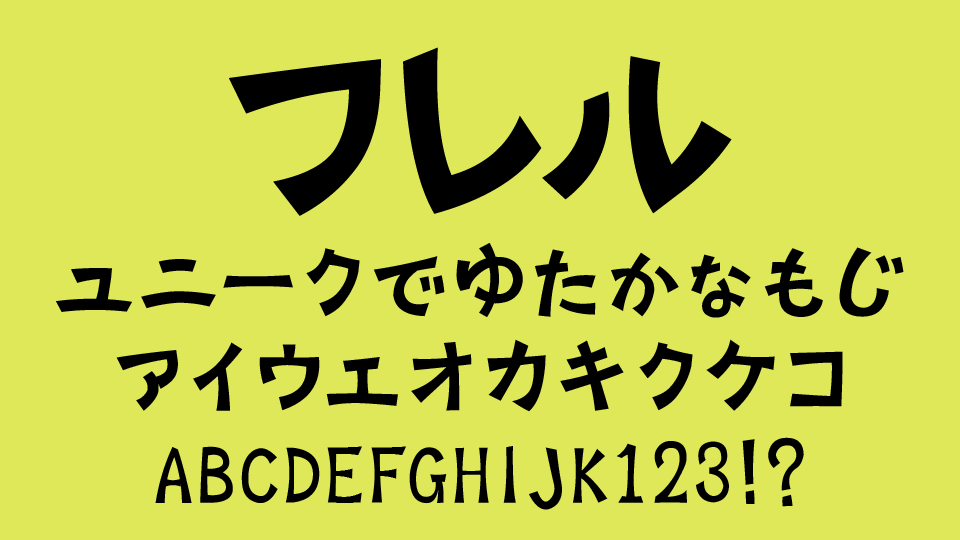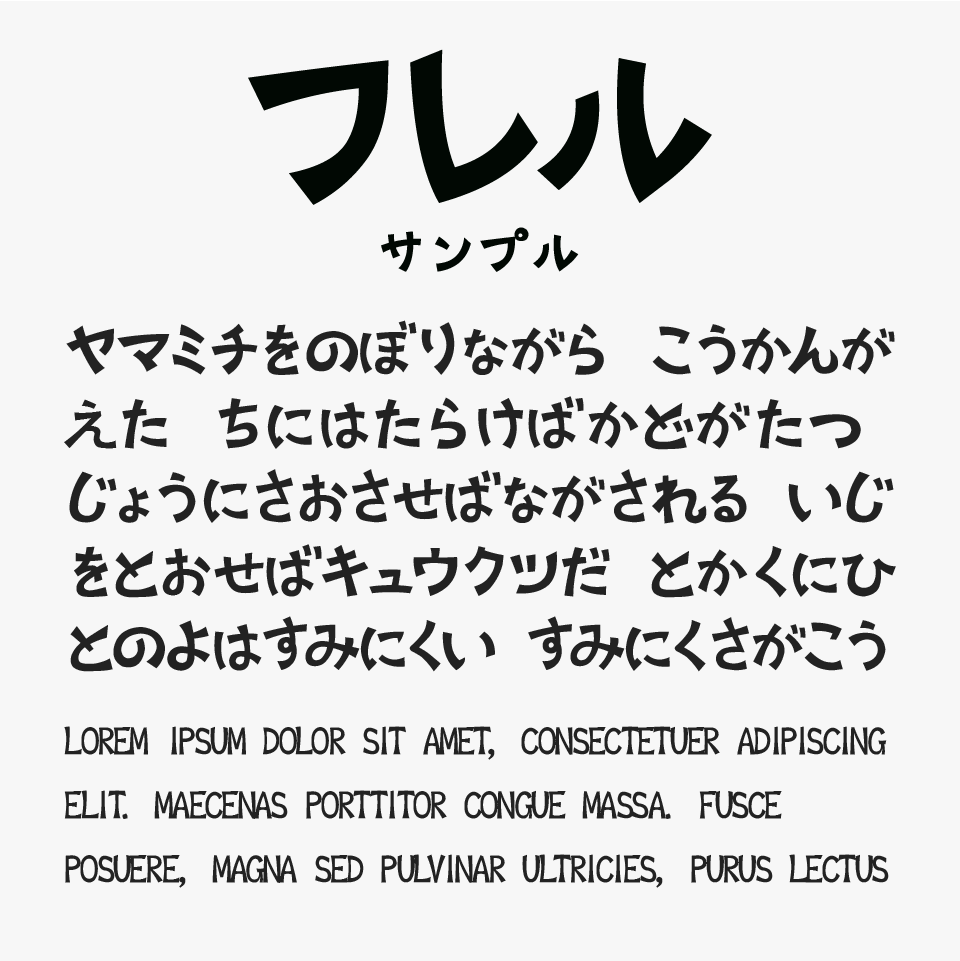
フレル
フレルフォントは、手書きっぽさのある丸くて太めのシルエットに、少し傾いた線や独特のカットを取り入れた、コミカルで親しみやすいデザインフォントです。
どっしりとした安定感がありながらも、文字全体にリズム感があり、見ているだけで楽しい雰囲気が感じられるフォントです。シンプルな字体で読みやすく、それでいてしっかりと個性が感じられるため、タイトルやロゴでも活躍できるフォントです。
子ども向けコンテンツやゲーム、YouTubeサムネイル、キャラクターロゴ、イベント告知など、明るくポップなデザインにぴったりなフォントです。可愛すぎず、ほどよく力強さもあるため、幅広い年代に向けたコミカルなデザインでも使いやすいフォントです。
収録文字は、ひらがな・カタカナ・アルファベット・数字・記号が収録されています。